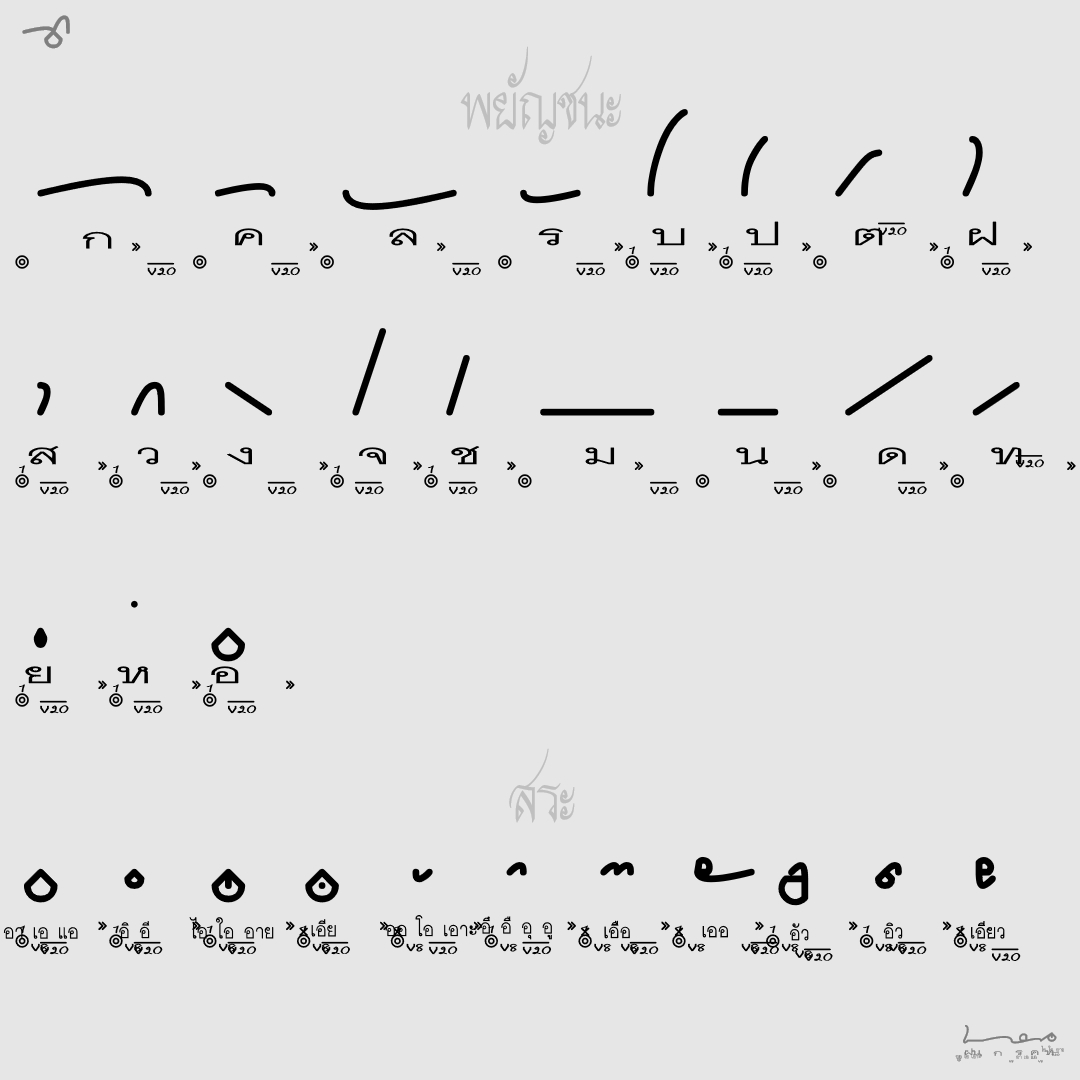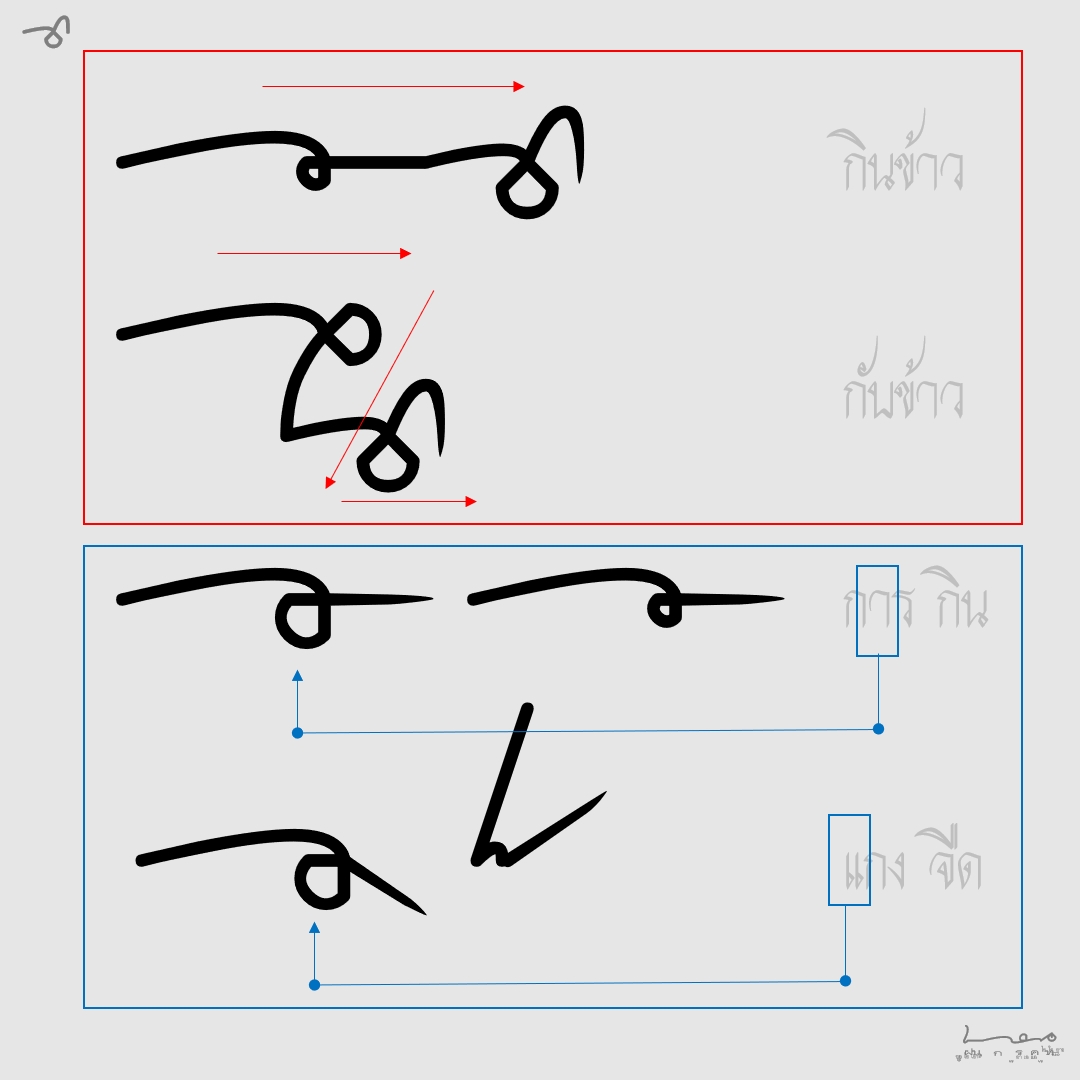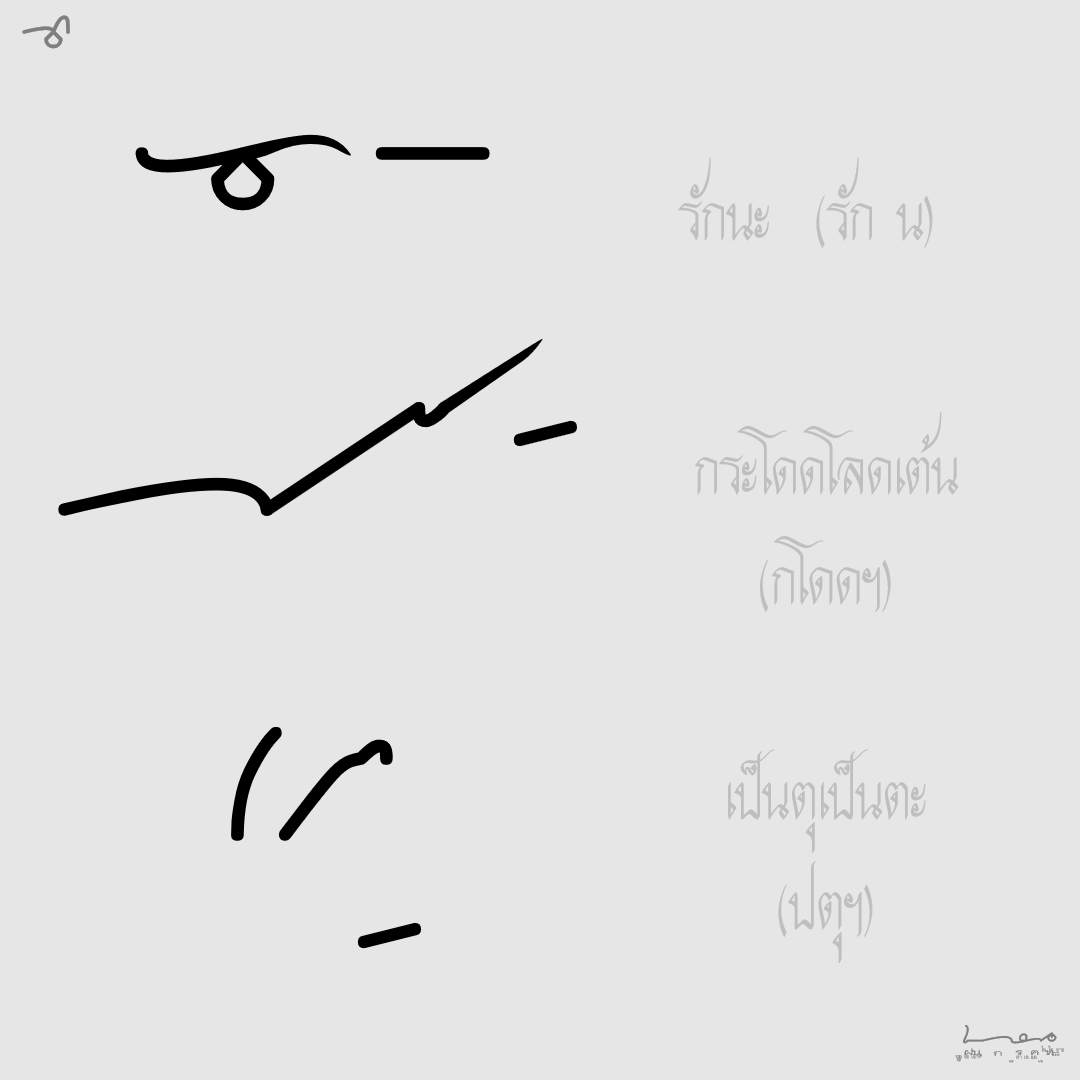
ฟอนต์ เกรกก์ไทย
ฟอนต์เกรกก์ไทย เป็นฟอนต์ทดลอง อักษรชวเลขแบบเกรกก์ ทำเสร็จไป 80% แต่คิดว่าพอก่อน..
ระดับความยากในการทำให้ 8 กระโหลก ใช้งานยากระดับ 5 ตัวอักษรไม่มีความกว้างต้องเคาะ space เอาเอง
และต้องศึกษาชวเลขก่อน ส่วนการอ่านถ้าชวเลขยังไม่คล่องใช้ตัวปรกติ ถ้าคล่องแล้วใช้ตัวหนา(กด bold)
ตัวอักษรชวเลข ถึงจะไม่เยอะ
แต่การเขียนไม่ง่าย ต้องเขียนเป็นคำสะกด
แต่..แต่ถ้าอย่างนั้น ชวเลข ก็จะไม่เร็วกว่าเขียนปรกติ ..จึงนิยมเขียนคำย่อ
ส่วนการย่อ ก็ต้องตามตำรา หรือตามที่ตกลงกัน ในกลุ่ม
ตัวอย่างนี้ ผมมั่วๆเองนะครับ อย่าเอาไปอ้างอิง
ฟอนต์เกรกก์ไทย เป็นฟอนต์ทดลอง อักษรชวเลขแบบเกรกก์ ทำเสร็จไป 80% แต่คิดว่าพอก่อน..
ตัวอักษรไม่มีความกว้างต้องเคาะ space ให้เลยตัวอักษรที่เห็นเอาเอง และต้องศึกษาชวเลขก่อน ส่วนการอ่านถ้าชวเลขยังไม่คล่องใช้ตัวปรกติ ถ้าคล่องแล้วใช้ตัวหนา(กด bold)
2 เรื่องกินกระโหลก
1. สีน้ำเงิน  ต้องสลับ สระ ตัวหน้า มาไว้ข้างหลังพยัญชนะ --> 3 กระโหลก
เนื่องด้วยวรรณยุกต์ไม่จำเป็นต้องใช้ในชวเลข ก็เลยจะใช้วิธี รวบอักษรละลายตัววรรณยุกต์ไปเลย จะได้ทำ function swap พยัญชะ กับสระ ได้ง่ายขึ้น(โดยไม่ต้องเผื่อการมีวรรณยุกต์) .. จบได้ด้วยดีใน fontforge ..แต่ดีที่เอามาทดสอบใน MS excel --> พังจ้า!!  ต้องกลับไปเขียนใหม่หมด..ใช้วิธีแบบตอนทำฟอนต์อักษรเบรลล์
2. สีแดง flow ของตัวอักษร ไปข้างหน้า และถอยหลังได้ แถมด้วย ขึ้นลงได้อีกด้วย --> 5 กระโหลก
ความต้องการคือ ย้ายตำแหน่งต้นอักษร ไปต่อกับปลายอักษรตัวก่อน วิธีที่ง่ายที่สุดคือ ใช้ระบบ mark ช่วยเหมือน สระ วรรณยุกต์ แต่ไม่ใช้บนล่าง แต่เป็นซ้ายขวา  ไปได้ดีใน fontforge แต่เหมือนเดิม MS excel พังอีกแล้วจ้า ไม่ยอมเลย จะทำได้ต้องเป็น สระ (mark ไม่ใช่ gryph) เท่านั้น ..แต่ พอเป็น สระ ..พัง 2  1. เรื่องความกว้างของตัวอักษรกะกลายเป็น 0 ทันที 2. เรื่องจะมีสระโดยไม่มีพยัญชนะ ไม่ได้!! อันนี้พอแก้ไขได้หาเงื่อนไขเพื่อจะรู้ว่าอักษรตัวนี้เป็นตัวแรก ถ้าเป็นตัวแรกก็แทรก พยัญชนะเข้าไป ถ้าไม่ใช่ก็เป็นสระตามเดิม ส่วนเรื่องความกว้างเป็น 0 อันนี้ยังแก้ไม่ได้ ..รบกวนให้ผู้ใช้เคาะ space เอาเองครับ